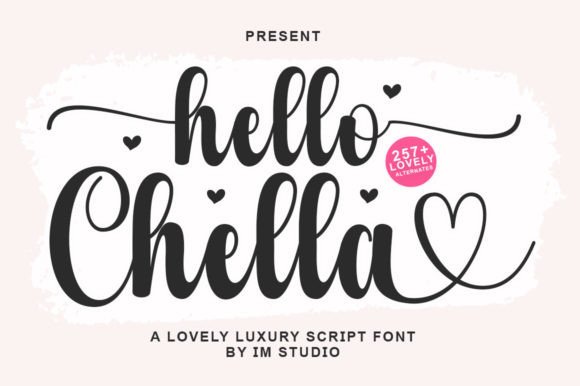
Hello Chella
إذا كنت تبحث عن أصول عالية الجودة مثل Hello Chella، فإن هذه الحزمة المميزة هي خيار رائع لمشاريعك الإبداعية.
سواء كنت تقوم بإنشاء منتجات الطباعة عند الطلب أو دعوات الزفاف أو رسومات وسائل التواصل الاجتماعي، فإن Hello Chella هو الخيار المثالي.